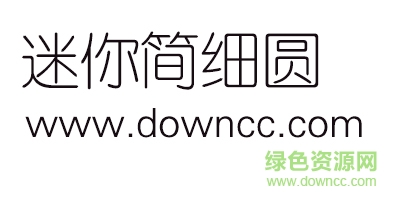
迷你簡細圓是迷你字體庫中的一種經(jīng)典字體,本字體完全免費使用!這款字體適合用于藝術(shù)策劃、廣告制作等方面,使用范圍非常廣泛!喜歡的朋友們歡迎來綠色資源網(wǎng)下載體驗喲!
迷你簡細圓是一款應(yīng)用于設(shè)計方面的中文簡體漢字,該字體纖細大方得體,整體風格非常出色,并且字庫完整,可以適用于名片設(shè)計、平面設(shè)計、廣告設(shè)計、報紙雜志等領(lǐng)域。
1.字體清晰、端正、嚴肅
2.拐角處、筆畫末端為圓弧狀